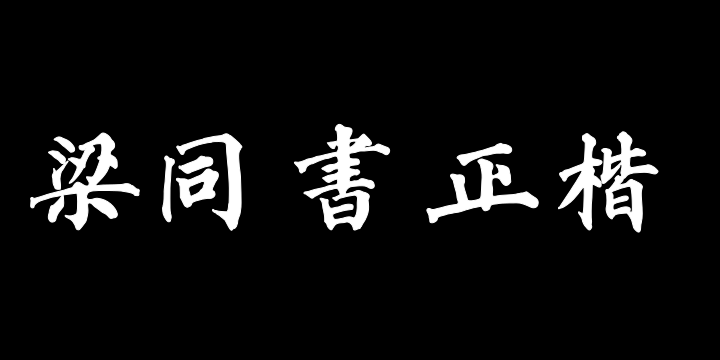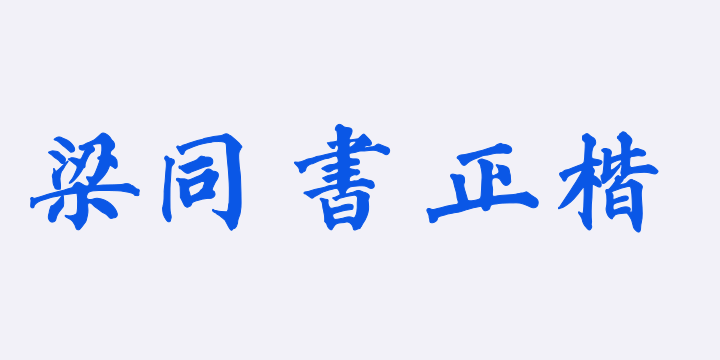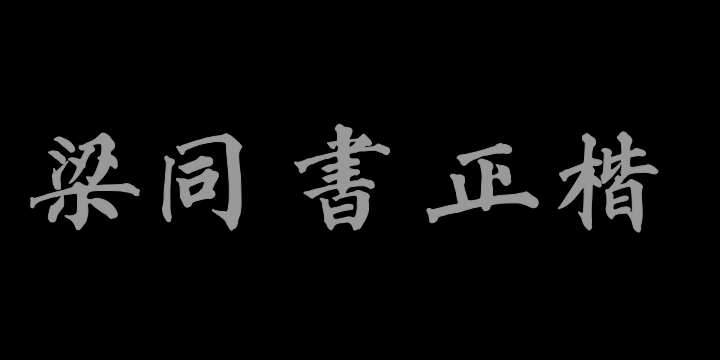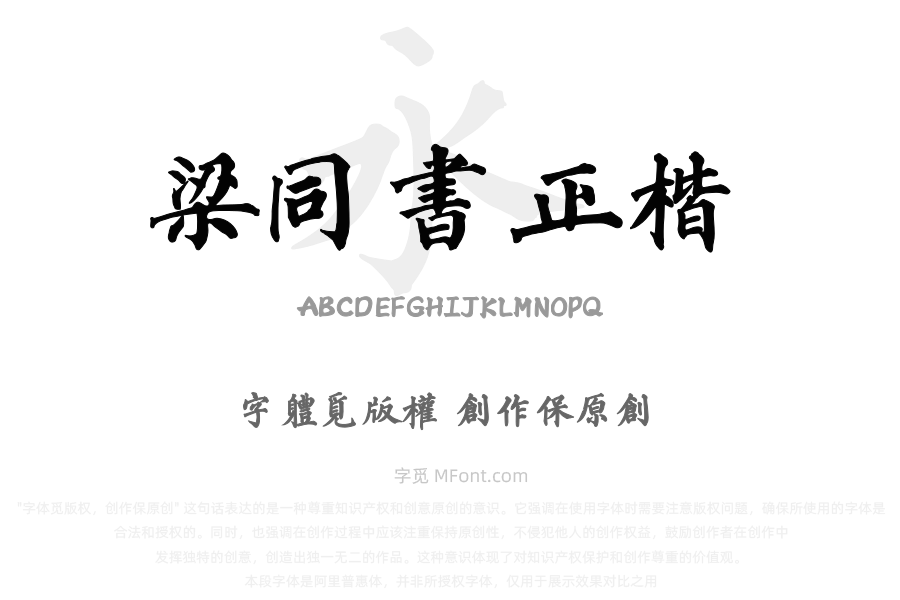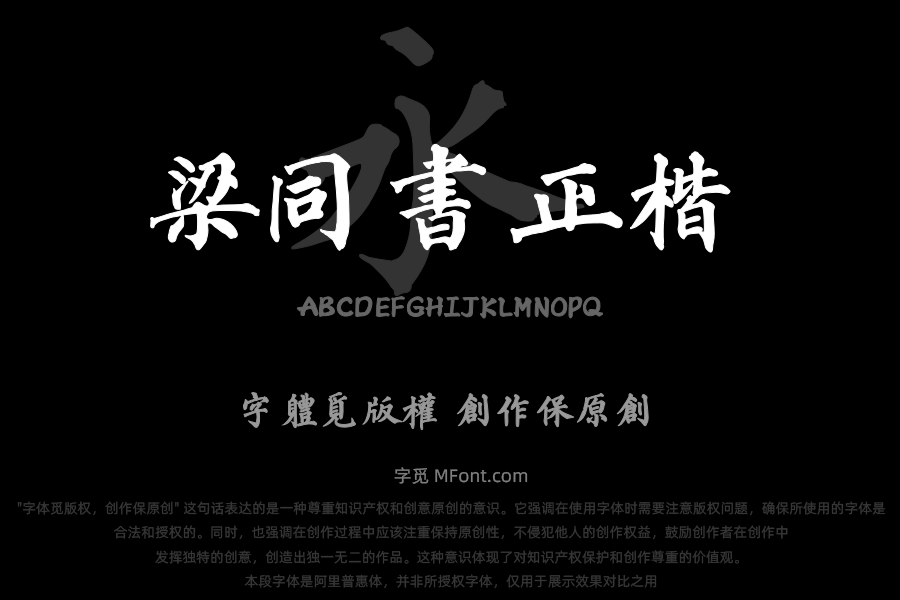
关于东篱山舟梁同书正楷繁体字体字库信息
字体全名: 东篱山舟梁同书正楷繁体
铸字厂: 东篱字库
设计师: 青岛东篱意境设计有限公司
字体简介: 东篱山舟梁同书正楷|淡墨轻岚,笔走千年文脉以清代帖学宗师梁同书六十年笔墨精髓为魂,「山舟正楷」,再现“端雅冲和,清劲秀逸”的文人风骨。字体承袭颜柳筋骨,融赵董灵韵,长锋软毫蘸饱淡墨,笔走龙蛇间,既有颜体的宽博结体,又见米芾的跌宕使转。每一笔提按皆含“疏可走马,密不透风”的韵律,淡墨洇染处如云雾缭绕,浓墨重按处似松柏挺立,尽显“淡墨探花”的雅致。字形端严中见灵动,楷书如《三味书屋》匾额,四字榜书结体紧严而气韵生动。